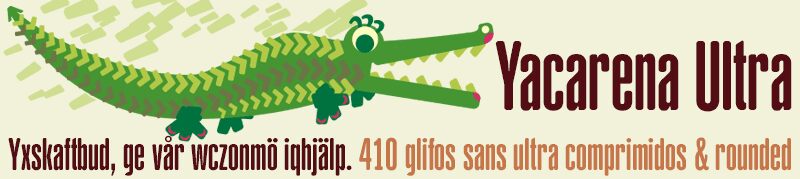
Yacarena Ultra es un proyecto tipogrfico surgido de mi necesidad redundante de disponer de una fuente muy condensada para ciertos trabajos de diseo grfico donde la cantidad de texto en grandes ttulos complican la composicin.
Yacarena Ultra is a typographic project emerged from my redundant to have a very condensed font for some graphic design work where the amount of text in large titles need complicated composition.
Tipografía Sans Ultra comprensada con acabado redondeado.